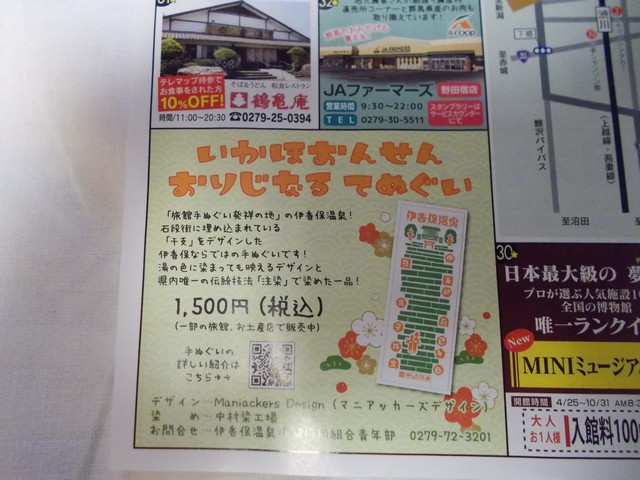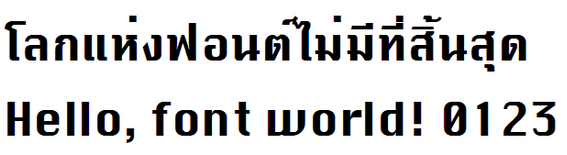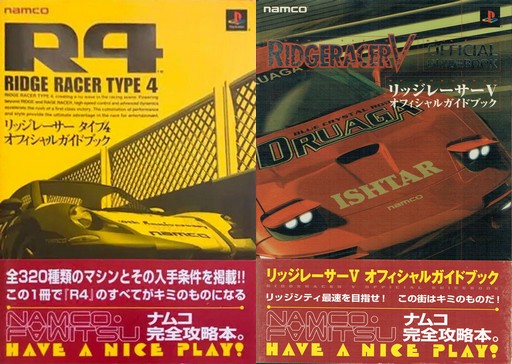
Chicago
- ©Apple
- Mac OS 8システムフォント
- 元はビットマップフォント
- 0に斜線が入る等、システムフォントのための配慮がなされている
Krungthep
- ©Apple
- macOS付属
- タイ語フォント
- 英字部分がChicagoと同じ
Chicagothic
- ©BRIDGEco. by Jin Hashiba
- BRIDGEco.
- カタカナ(1byte)
- 『Chicago』に合うカタカナ書体
Chicagothic2by3
- ©Apple Computer, BRIDGEco., IPA, 武蔵システム
- 組み合わせてみた
- 英数字『Chicago』
- カタカナ『Chicagothic』
- その他『TTEdit2/3ゴシック』bold
Handel Gothic BT
- ©Bitstream
- 書籍『TrueTypeフォントパーフェクトコレクション』収録
- 英数字
- 「コンチネンタル航空のフォントをつくってほしい」というDon Handelの依頼で作成
- SUPER FAMICOMのロゴの元になった書体
Strongcil
- ©Honey&Death
- OFGH&D
- Strongな感じのStencil書体
- プリントしたものをカットしやすいように、すべて直線で構成
WLG Barrel Stencil
なつみかん
- ©Gray Graphics
- Gray Graphics(閉鎖)
- ひらがな(1byte)、カタカナ(1byte)
- 久米田康治『さよなら絶望先生』の「さよなら」部分
GrayGraphics+
- ©Gray Graphics, coz, MM
- Gray Graphics(閉鎖)
- 組み合わせてみた
- ひらがな『みけ』
- カタカナ『CandyStore』
- 英数字『FancyBomb』
- 漢字『Rounded M+ 1p black』
FZぱひゃ丸かな
FZぱひゃ丸+
- ©108号, coz, MM
- 組み合わせてみた
- 仮名、英数字『FZぱひゃ丸かな』
- 漢字『Rounded M+ 1p medium』
- 合うという意味では『DFPブラッシュRD』なんかが良いのかも
- ただそうすると『FZぱひゃ丸かな』の面白味が埋もれてしまうかな、と
FZゴンタかな
はらませにゃんこ
- ©稲塚 春
- 森の中の猫の小屋
- ひらがな、カタカナ
- 「まるみ」版あり
- ロゴでの利用を想定した手作り書体
アンニャントロマン
- ©Inatsuka Haru
- 森の中の猫の小屋
- ひらがな、カタカナ、英数字
- ロゴでの利用を想定した手作り書体
えれがんと-W9
- ©佐藤豊/タイプラボ
- タイプラボ
- 4 weight
- ひらがな、カタカナ
- 細いヨコ線と太めのタテ線でスキッと処理
源暎ロマンのーと W9
- ©おたもん
- 御琥祢屋
- 英数字
- タイプラボ『えれがんと』と一緒に使える欧文書体
源えれがんと(ElegantHanRoman)
- ©佐藤豊、おたもん、Adobe
- 組み合わせてみた
- 仮名『えれがんと-W9』
- 英数字『源暎ロマンのーと W9』
- 漢字『源ノ明朝 Bold』
飴色フォント
- ©るり
- S*crown
- 教育漢字を中心とした一部の漢字まで
- 飴で書いたような柔らかな書体
PtO-うたミン小2
- ©ぱれったいぷ
- BOOTH
- 小2で習う漢字まで
- 歌う文字というコンセプト
晩秋レトロミン
- ©すずみばと書林
- BOOTH
- 教育漢字+α
- レトロな雰囲気と明朝体のような特徴を併せもつ、クセの強い書体
- 見出し向けフォント
みつバッチフォント
- ©キユマヤ園
- びゅんびゅん→SSS
- 漢字176文字
- ハニカム形の六角形を文字にあてこんだ書体
数式フォント
- ©キユマヤ園
- びゅんびゅん→SSS
- 教育漢字+第1水準途中まで
- 図式の記号を随所に取り入れた書体
おこのみフォント
- ©FLOP DESIGN
- FLOP DESIGN
- ひらがな、カタカナ、英数字
みんなのうた
- ©Maniackers Design Masayuki sato+Tsuyoshi Nagae
- Maniackers Design
- ひらがな(1byte)、カタカナ(1byte)、英数字
- テレビ番組『みんなのうた』に合うようなフォント
- 楽しくて懐かしくて、どこか淋しさの残る独特な世界観
いかほ
Chain Reaction
- KyA